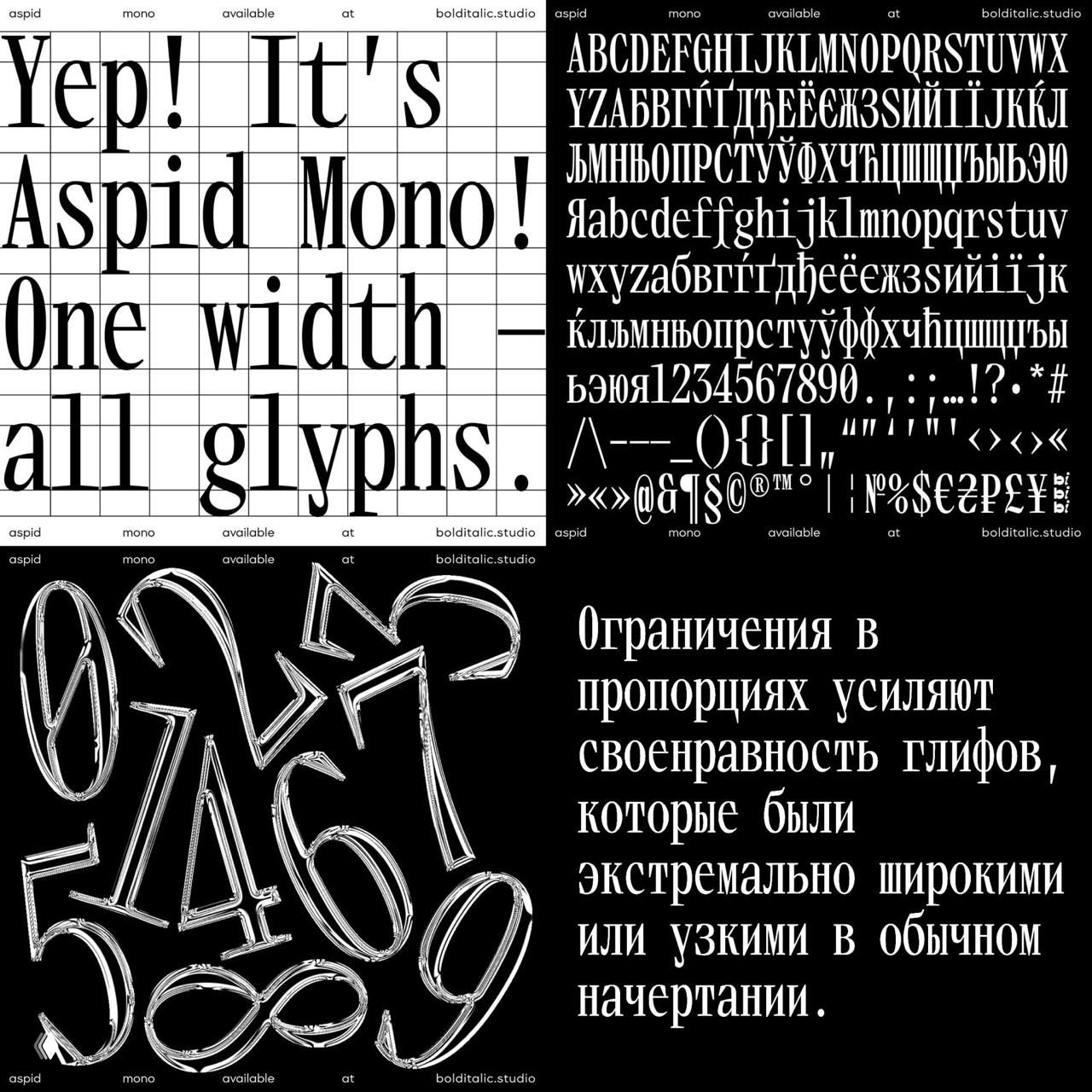
Aspid Mono — редкая моноширинная антиква
Редкая моноширинная антиква с харизматичными острыми засечками и лёгкой декоративностью. Знаки вытянуты по высоте, что делает шрифт идеальным для громких заголовков на плакатах или сайтах.
Демонстрационный лист шрифта Aspid Mono: примеры кириллических и латинских глифов, цифр и образцы заголовков на контрастном фоне.
Примеры глифов и композиционные образцы шрифта Aspid Mono.